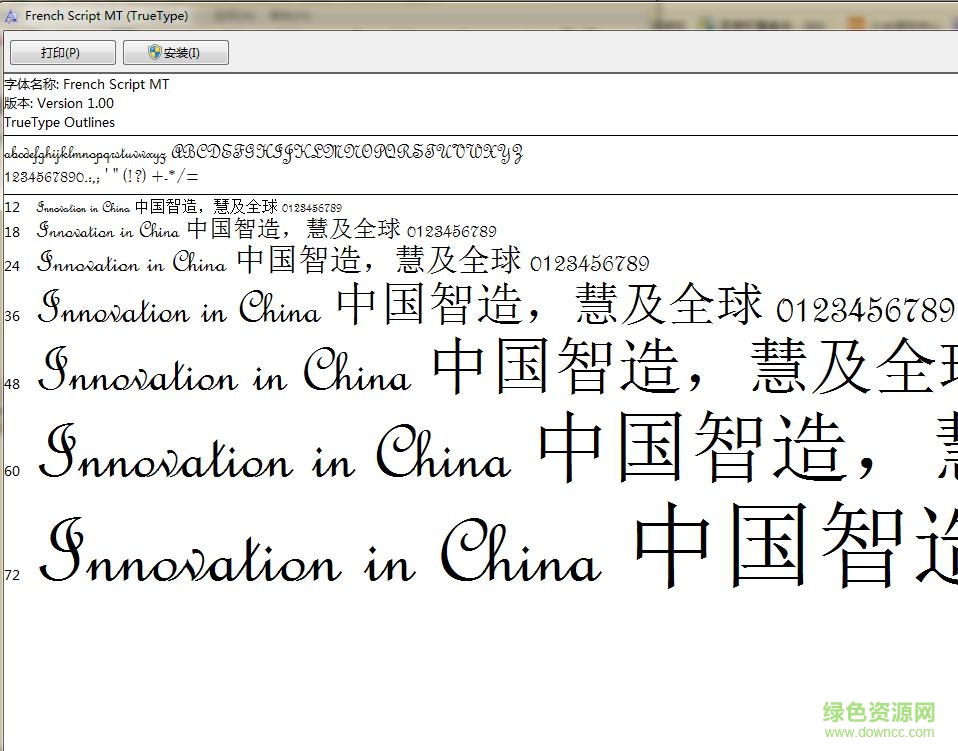
1、西方字体的开端从15世纪中期 (1400年) 开始,意大利开始了文艺复兴运动。约1465年,印刷工人开始使用了模仿知识分子和抄写员手写的字体进行印刷,与早期古腾堡印刷使用的 Blackletter 划清界限。
2、关于英文字体,对网页设计师朋友们来说一定并不陌生,即使我们很少做英文语系的网站,但在浏览国外网站的时候,大家一定都会有或多或少的认识。
3、英文文字大致分成三类,衬线体,无衬线体和其他字体。其他字体包括哥特体,手写体和装饰体,这些字体在我们工作中使用相对较少,所以重点介绍衬线体和无衬线体两大类。